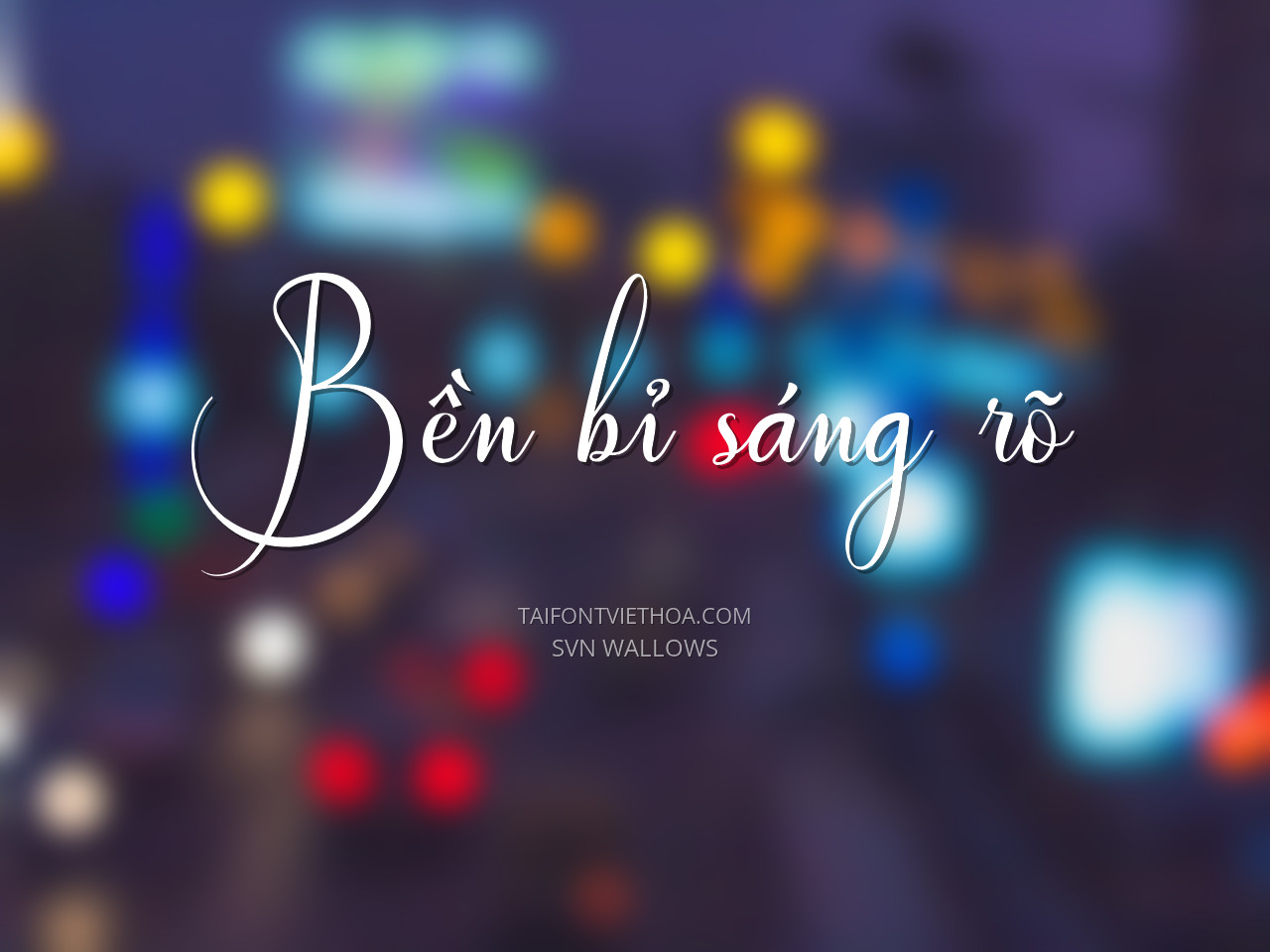
Font việt hóa SVN Wallows
Giới thiệu về Wallows – Phông chữ script brush phóng khoáng
Wallows Typeface là phông chữ viết tay gốc do Kodhi Banks(Banks Studio, Indonesia) thiết kế và phát hành lần đầu năm 2015 trên Creative Market. Font gốc gây ấn tượng mạnh nhờ phong cách brush tự nhiên, các nét thanh – đậm biến đổi linh hoạt, tạo hiệu ứng lượn sóng vui tươi nhưng vẫn đảm bảo độ rõ ràng khi sử dụng cho tiêu đề hoặc thương hiệu. Với khả năng hỗ trợ hơn 60 ngôn ngữ Latinvà ký tự đặc biệt, Wallows trở thành lựa chọn quen thuộc trong cộng đồng thiết kế quốc tế.
Phiên bản SVN Wallowsđã được Styleno.1 FontsViệt hóa toàn diện, bổ sung đủ dấu tiếng Việt, cân chỉnh lại kerning cùng hinting để giữ nét mượt mà ở mọi cỡ chữ. Các glyph Việt hóa được tối ưu cho văn bản dài, không lỗi dấu, không vỡ nét dù dùng trên màn hình retina hoặc khi in ấn chất lượng cao. Đội ngũ taifontviethoa.comđã kiểm thử thực tế trên nhiều nền tảng thiết kế như Photoshop, Illustrator, Canva trước khi chia sẻ miễn phí cho cộng đồng, giúp bạn dễ dàng sử dụng cho mọi dự án mà không lo lỗi font.
Đặc điểm thiết kế, ứng dụng và ngành nghề phù hợp của Wallows
Wallows thuộc nhóm script brushvới nét bút nghiêng khoảng 12 độ, kết hợp bounce baselinenhẹ làm cho dòng chữ như đang chuyển động nhảy múa trên trang giấy. Độ tương phản nét được xử lý vừa phải, phù hợp cả khi dùng lớn làm tiêu đề hoặc làm text trang trí trên poster, banner. Font có sẵn bộ ligaturecho các cặp chữ đặc biệt như tt, th, ll giúp chữ nối liền mạch, cùng với các alternates(chữ cái thay thế) và swashtrang trí giúp designer tạo điểm nhấn sinh động, cá tính.
Ứng dụng tiêu biểu
– Logo & Branding:Phù hợp cho thương hiệu handmade, quán café, bakery, beauty shop, studio ảnh cá tính.
– Ấn phẩm sự kiện:Poster lễ hội, banner quảng cáo, thư mời workshop, flyer sinh nhật, thiệp chúc mừng.
– Thiệp & nhãn mác:Thiệp cưới phong cách boho, sticker gói quà, nhãn sản phẩm thủ công.
Ngành nghề khuyên dùng
Wallows lý tưởng cho lĩnh vực F&B, Wedding Planner, Spa & Beauty, Handmade, Digital Agency, Studio nhiếp ảnh, shop thời trang trẻ trung hoặc vintage. Khi kết hợp với các font sans-serif hiện đại, Wallows giúp tiêu đề nổi bật mà vẫn cân bằng tổng thể thị giác. Tải ngay phiên bản Việt hóa tại taifontviethoa.com để tận hưởng trọn vẹn cá tính viết tay cho mọi dự án sáng tạo của bạn.